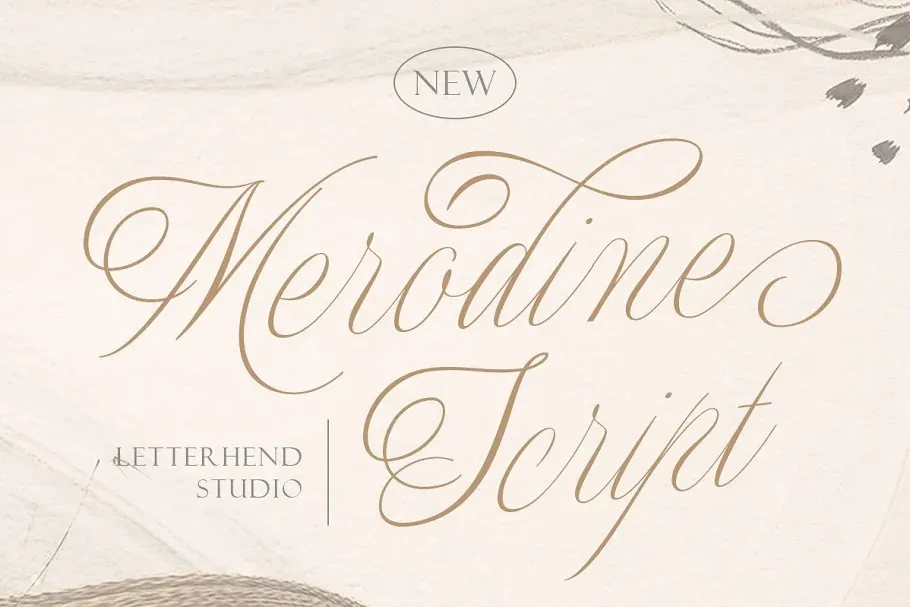
A Merodine Font é uma escolha perfeita para quem busca um estilo elegante e moderno. Desenvolvida pelo Letterhend Studio, esta fonte script possui um estilo gótico com traços finos, adicionando ao seu design um toque de elegância sofisticada. Ela se destaca como uma opção versátil para diversos ambientes: seja em anúncios, logotipos ou pequenos efeitos visuais. Uma característica interessante é a presença de alternativas estilísticas que permitem um grande nível de personalização, permitindo transformar o texto em formas únicas e atrativas. Seja para criar texturas elegantes para nomes ou criações gráficas criativas, esta fonte oferece uma variedade impressionante de possibilidades. Uma adição à sua coleção de fonts é algo que não pode ser negligenciado.